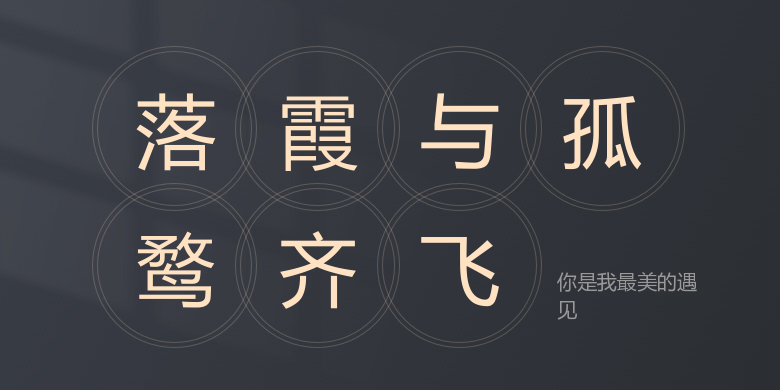
你是我最美的遇见
你是我最美的遇见,这款字体结构工整、笔画清晰,兼顾美观与易读性,适用于标题、正文、海报、包装、LOGO 等多种场景。字形优雅稳定,风格百搭耐看,适配日常排版与创意设计,让文字呈现更舒适、更具质感。你是我最美的遇见一笔一画,皆是细节,以均衡的比例、流畅的线条打造舒适视觉体验,字形端正大气,风格简约现代。无论是商业设计、品牌宣传还是日常排版,都能轻松驾驭,让文字更有格调与力量。你是我最美的遇见字体下载。